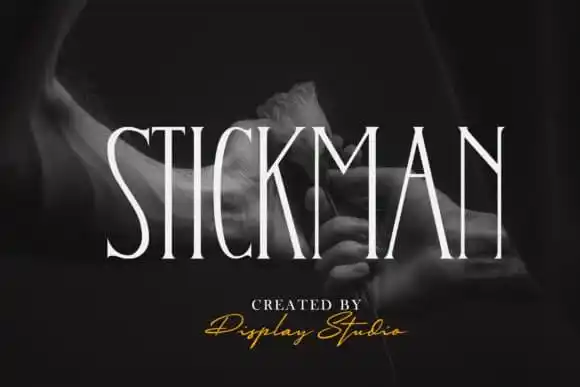
Stickman Display Font – Download Grátis
Introduzimos a Stickman Display Font, uma tipografia de exibição distintiva e elegante que combina influências tradicionais num estilo contemporâneo. Inspirada na arte e na beleza, esta fonte mantém detalhes latinos bem equilibrados contendo contrastes distintivos. Aproveite a Stickman para alcançar um look precioso e discreto, bem como máximo versatilidade. É perfeita para criar logos estilosos, edições poderosas, convites, citações gráficas e muito mais. Esta fonte é ideal para quem busca uma exibição única que não se limite a estereótipos convencionais. Com sua combinação de contraste elegante e equilíbrio dos detalhes latinos, você pode criar designs impressionantes que se destacam em qualquer cenário. Essa fonte não apenas oferece um visual atraente, mas também uma grande liberdade para adaptar ao seu gosto pessoal ou à necessidade específica de cada projeto. Agora é o momento de explorar e experimentar as possibilidades da Stickman Display Font – ela certamente vai impressionar você e seus projetos!